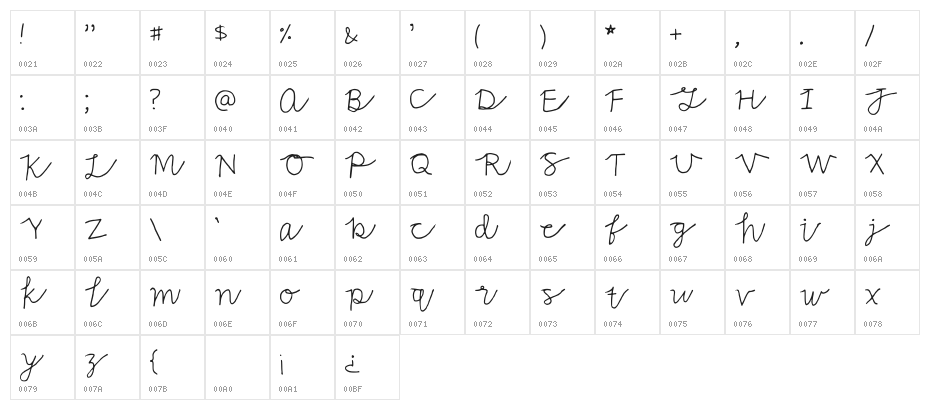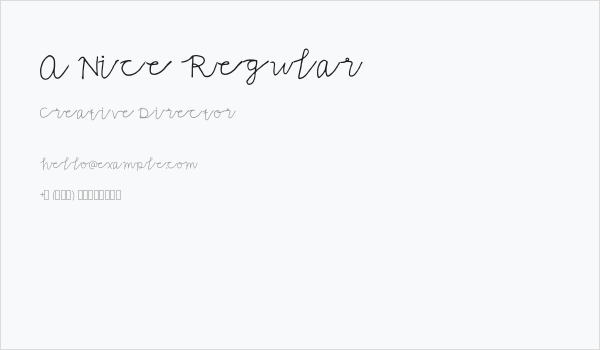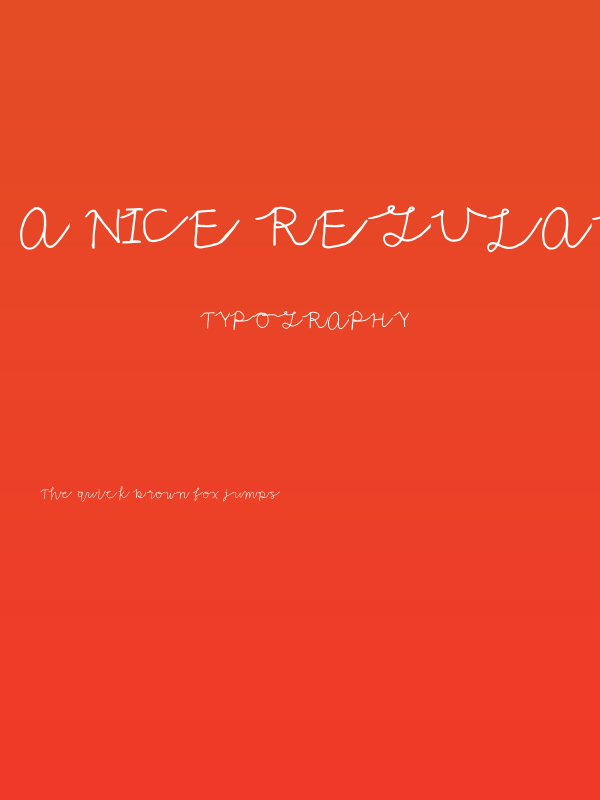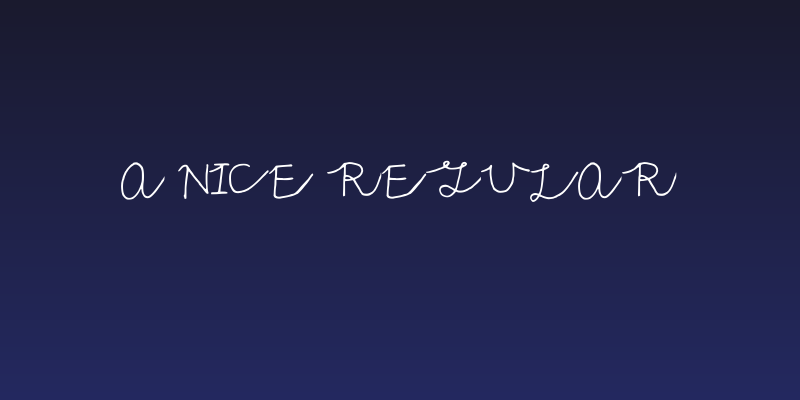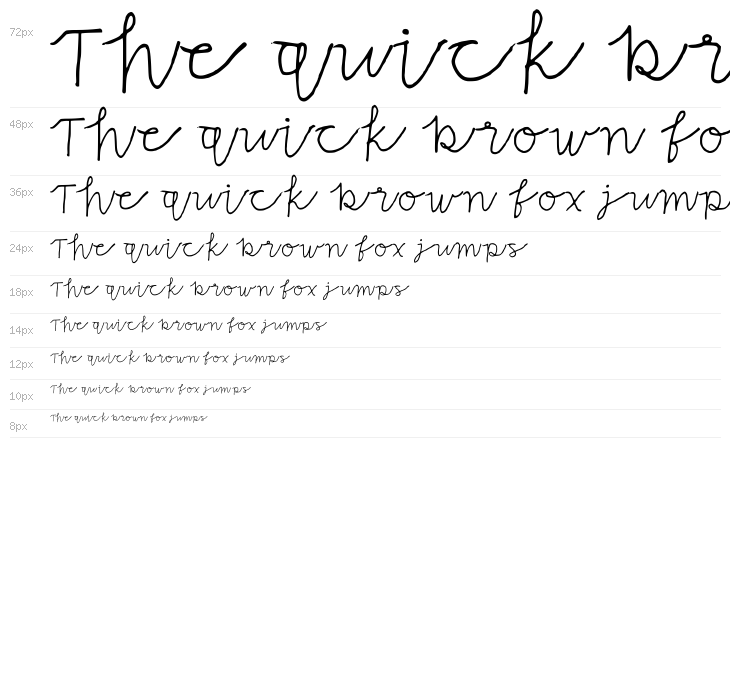
A Nice Regular Font
| Stile generale | Casual, Playful |
| Caso d'uso | Logos, Invitations, Greeting Cards |
| Progetti proposti | Ideal for greeting cards, personal invitations, creative branding, and informal digital content. |